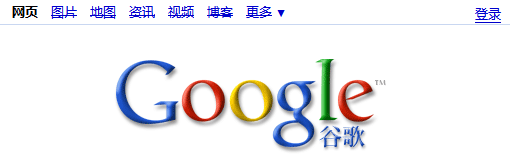
雅黑字体对IE显示网页布局的影响
5月微软正式提供了Windows XP下可用的雅黑字体。雅黑字体是一款近乎完美的字体,解决了宋体小文字无法辩认的问题,特别是对于液晶显示器(LCD),在开启ClearType效果之后,你就会得到一个更加完美的视觉享受。我现在已经对雅黑着迷了,回头看默认为宋体的系统,锯齿太明显了,很丑。
但是这样随之而来的问题是,雅黑字体会对Internet Explorer中的网页布局显示有一些错位影响。目前我发现的问题主要存在于两个方面。
一、下划线有时变成了删除线
其实这是一种视觉错位,并不是真正的删除线,在有英文和中文混排的段落中,下划线会被折断,变得相当不规则。
Google.cn首页的中文文字超级链接
这个现象只会出现在中文字体中,英文字体不受影响
如果有中英文混排的情况,就更加明显了
可以看出,有中文的地方下划线都上移的,英文没有受到影响。
二、Internet Explorer中行高有变化
我的博客中对一个有背景图片的超级链接的截图
原来在宋体下正常的样式,现在在下面露出来了一块,这说明在Internet Explorer中行高增加了。但是在Firefox中并没有发生变化。
三、尝试解决
在Google.cn的截图中我们发现,右边的“登录”超级链接是正常的,这说明不是所有的中文超级链接都存在这样的问题,我仔细对照了一下他们样式上的差异,发现左面的链接比右面的“登录”多了一个样式:
vertical-align:top;
我把这个属性屏蔽掉之后一切正常。两样在第三张来自“魅族论坛”的这张截图中,我发现在虽然它没有在文字样子中出现vertical-align,但是在后面的两个小图片中有:
vertical-align:middle;
去掉这两个图片后,一切又正常了。
因此可以肯定,在中文的超级链接中使用vertical-align会出现问题(并不是每个元素都有vertical-align属性),最简单的解决方法就是,避免使用vertical-align或者valign,或者避免使用超级链接的下划线。当然这不是正确处理问题的好方法。
至于在我博客中再现的这个问题,恰恰说明雅黑字体导致Internet Explorer(Firefox显示正常)中行高的增加,要解决这个问题,只需要控制得的高度就可以了,但是是一个行内元素,没能设置高度,所以要配合disaply:block,然后再固定高度(不过,设置了block属性之后可能会产生自动换行,这时候你就要结合使用float等属性了)。我发现这个方法也能解决上面的问题,所以为超级链接固定高度会是比较好的方法。
额外说明:我是在Windows XP的基础上修改了默认字体,可能会因此而产生一些问题,上面我列举的两类问题我很难断定是由于雅黑字体本身引起的,还是其它不正确设置引起的。暂时没有找到Vista系统测试是否同样存在这样的问题,如果哪位有条件可以帮忙测试一下。
注:这个问题存在于Internet Explorer的各个版本中,Firefox不受影响。
附一网友的评论,不知有无道理:“这是浏览器对样式表解析而产生的差异。跟字体没有多大关系。...”